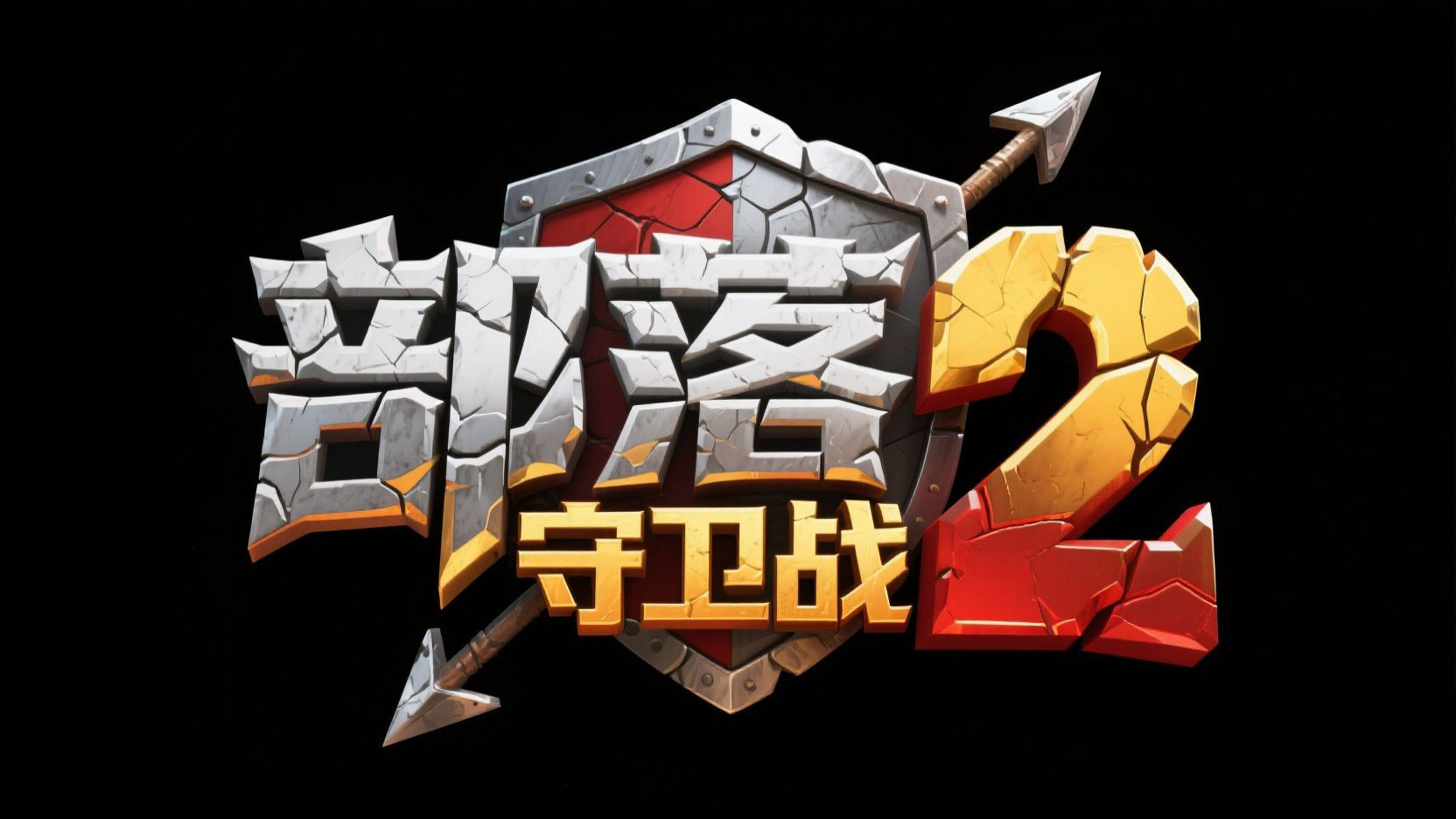
创作一个游戏艺术标题 “部落 守卫战 2”,“部落” ...
创作一个游戏艺术标题 “部落 守卫战 2”,“部落” ...AI字体提示词
风格定位
适合做风格探索与字形灵感延展。
适合场景
海报设计、品牌标题、电商设计、创意视觉
创作一个游戏艺术标题 “部落 守卫战 2”,“部落” 用仿石质字体,笔画带石材质感细节,灰白渐变;“守卫战” 用金属质感字体,笔画粗壮有力,金黄渐变;“2” 用红色立体字体。标题背后融入一个盾牌、箭头元素,营造坚硬稳固、充满力量感的游戏风格。正视图,背景为干净的黑色。
可替换关键词
金属纸张肌理浮雕高对比立体阴影强笔触“部落守卫战2”“部落”
生成建议
• 先保留核心风格词,再替换材质、颜色和光影词做多轮尝试。
• 如果用于品牌标题字,补充品牌气质、行业属性和情绪关键词。
• 如果用于海报或电商标题,额外强调大字、对比度和视觉冲击力。